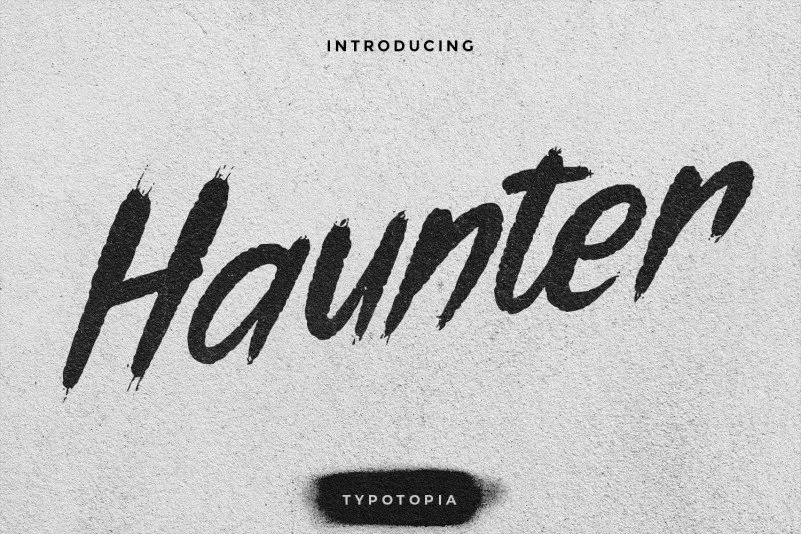
Haunter Display Font – Download Grátis
Haunter Display Font é uma bela escolha para qualquer projeto que busca destaque visual inusitado e interessante. Inspirada no estilo de pintura à esmalte, essa fonte de exibição apresenta um acabamento cuidadosamente detalhado, com traços brilhantes e movimentos fluidos, que criam um efeito único e atraente. Ela é perfeita para nomes de marca, posters promocionais, logotipos e qualquer outro elemento visual que deseja dar um toque vibrante e chamativo à sua peça. Desenvolvida pela typotopia, Haunter Display Font oferece uma experiência única de design, com suas linhas elegantes e movimentos fluidos criando texturas e padrões impressionantes que são ótimos para destacar qualquer arte digital ou impressão.